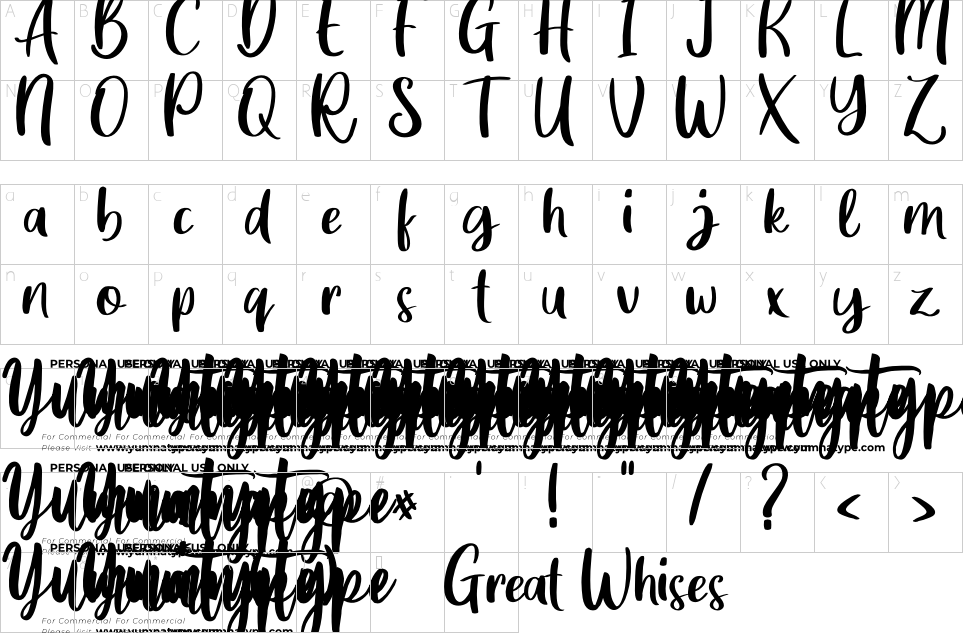
Descubra a delícia e a variedade de Great Wishes Font, uma fonte livre e gratuita disponível para Windows e Mac. Esta elegante fonte foi criada pelo designer Yumna Type e já foi baixada 5888 vezes. Se você está em busca de uma maneira criativa de enriquecer o design do seu próximo projeto com um ar suave e alegre, Great Wishes é perfeito para você. Sua simplicidade e facilidade na legibilidade complementam bem qualquer estilo gráfico, desde ilustrações até logotipos modernos. Com uma variedade de opções para personalizar, esta fonte certamente se tornará um dos seus favoritos. Descubra por que tantos designers já aderiram a Great Wishes Font e estejam tentados a adicioná-la à sua coleção de fontes.